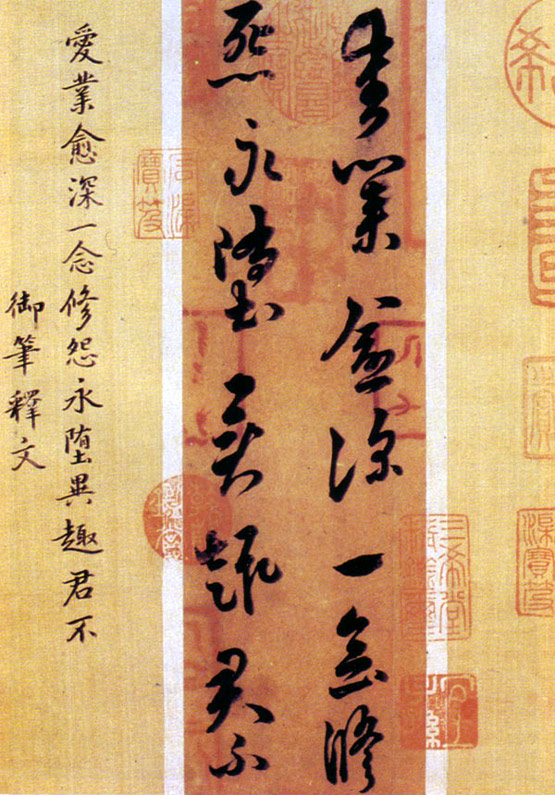
萧衍
萧衍简介
梁武帝,南朝梁的开国皇帝。字叔达,南兰陵中都里(现江苏武进县)人。他原来是南朝齐的官员,南齐末年,出为雍州刺史,镇守襄阳,乘机打造兵器,整治舟船,静等天下大变。齐永元二年(公元500年),以讨伐东昏侯萧宝卷为名,举兵攻入建康城,掌握南齐王朝的实权。齐中兴二年(公元502年)迫使齐和帝禅位于己,正式称帝。萧衍在位48年,国家在政治、经济、军事、文化各方面都有发展。他颁布法令,禁止向官吏献礼行贿,积极倡导纳谏,对官吏进行监督。注重兴修水利,奖励农耕,减免赋税,减轻劳役,百姓安居乐业。建国学,开五经馆,修孔庙,亲自为太学生讲课,著述《孝经义》、《周易六十卦》等二百余卷。梁武帝统治时期,是南朝历史上最为稳定富足的几十年。
梁武帝尊儒崇佛,立佛教为国教,大建寺庙。他不但广建佛寺,而且为了替建康的僧人募化,三次舍身同泰寺,让臣下以数亿钱赎回。“南朝四百八十寺,多少楼台烟雨中”,是当时建康城内众多佛寺的写照。他还组织人马,举行辩论,攻击无神论者范缜及其神灭论思想。
太清二年(公元549年),降将侯景叛乱,攻破建康宫城一台城。梁武帝被囚禁在净居殿,仍念经不辍。四月,忧愤饥饿而死。
梁武帝博学多通,文武兼备。长于文学,善音律,工书法。《梁书刘孝绰传》称其“雅好虫篆”。唐代张怀瓘《书断》称:“帝好草书,状貌亦古,乏于筋力,既无奇姿异态,有减于齐高矣。”萧衍惟重钟繇、王献之,对钟繇、王羲之书法艺术成就,颇有精到之见。他把“殆同机神"作为书学批评标准,不仅开唐人、王羲之之先声,重要的是为品评书法确立了一项重神韵的审美法则,从而也确立了他自己在书法史上的地位。 著有《观锺繇书法十二意》、《草书状》、《古今书人优劣评》、《书评》等书论四篇。
传世书迹有《异趣帖》近于章草:“爱业愈深,一念修怨,永堕异趣,君不......”此帖清时入于内府。对其作者,向有萧衍和王献之两说,以倾向前者为多,明董其昌断为萧衍作品。